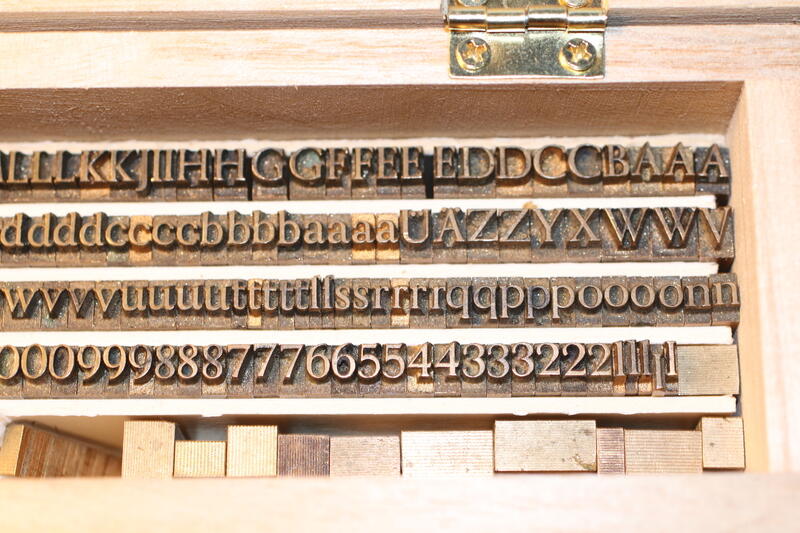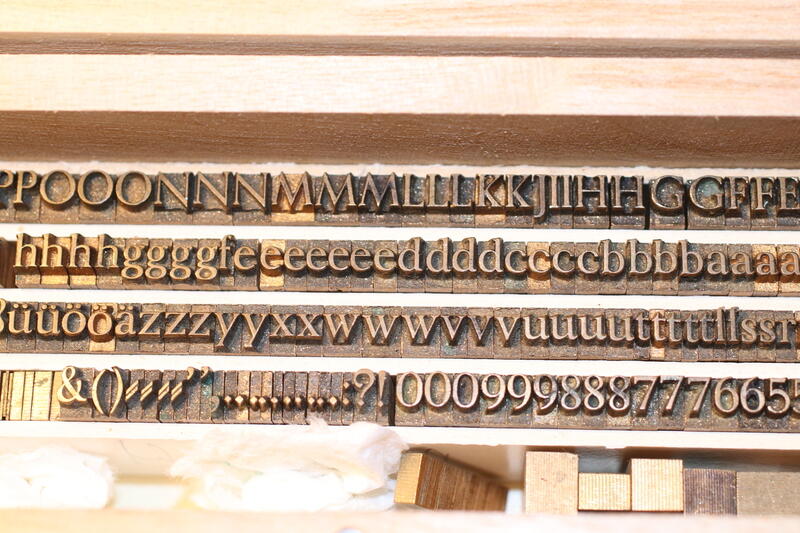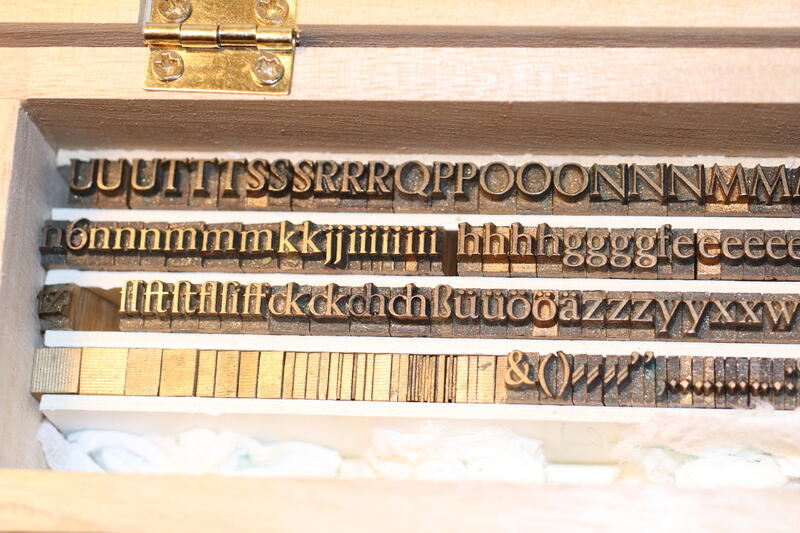
Prägeschrift für Vergolder oder Buchbinder
Ich habe mal wieder eine Prägeschrift für Buchbinder aufgegabelt. Es sind Messing-Hochkegel in Schriftgröße 16 - Versalien und Gemeine. Interessant ist, dass viele Ligaturen und sogar das lange s dabei ist. Leider fehlt das kleine l, dessen Aussehen man aus Ligaturen erahnen kann. Das Alter der Schrift kann ich nicht schätzen, aber der Umstand, dass ein langes s dabei ist, sagt mir, dass sie schon mehrere Jahrzehnte wenn nicht sogar über 100 Jahre alt sein könnte. Das Aussehen des kleinen »a« erinnert mich an die bekannte Baskerville, aber das große »Q« passt nicht dazu. Kann jemand sagen, welche Schriftart das ist? Mich interessiert das primär aus Neugierde aber auch um überhaupt die Aussicht zu haben, an passende kleine l heranzukommen.
Die Photos sind gespiegelt, um das Auswerten einfacher zu machen.